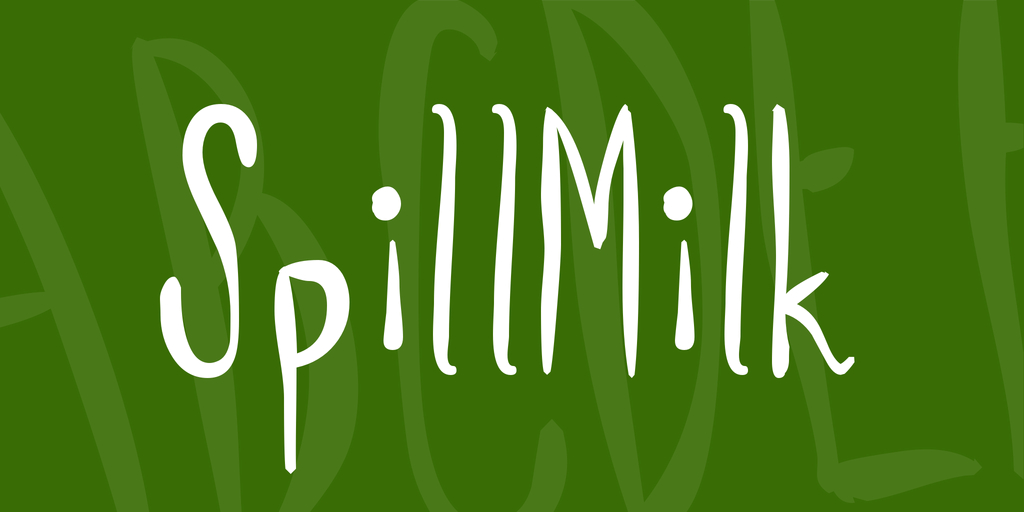
A fonte SpillMilk Font é perfeita para designers que buscam um estilo script fluido e elegante. Ideal para aplicativos digitais ou designs gráficos, sua tipografia se destaca por seu ar maciço e natural, com traços leves e curvas suaves. Foi projetada pelo designer Hamilton, a fonte SpillMilk é perfeitamente adaptável às necessidades de qualquer projeto editorial. Seja para criar um e-mail elegante ou personalizar anúncios com o seu toque único, a SpillMilk Font oferece uma solução gráfica que se adapta aos mais variados estilos. Com sua tipografia fluida e arredondada, a SpillMilk permite que seus designs tenham um ar de criatividade sem perder a elegância. Seja para assinaturas de e-mail, rótulos de pacotes ou até mesmo as capas de seu próximo design gráfico, a fonte SpillMilk é uma escolha ótima. Ela oferece uma grande flexibilidade no uso da tipografia, desde pequenos detalhes em textos interativos até grandes títulos em cartazes publicitários. A SpillMilk Font não só torna seus projetos mais atraentes, mas também adiciona um toque personalizado e sofisticado aos designs digitais.